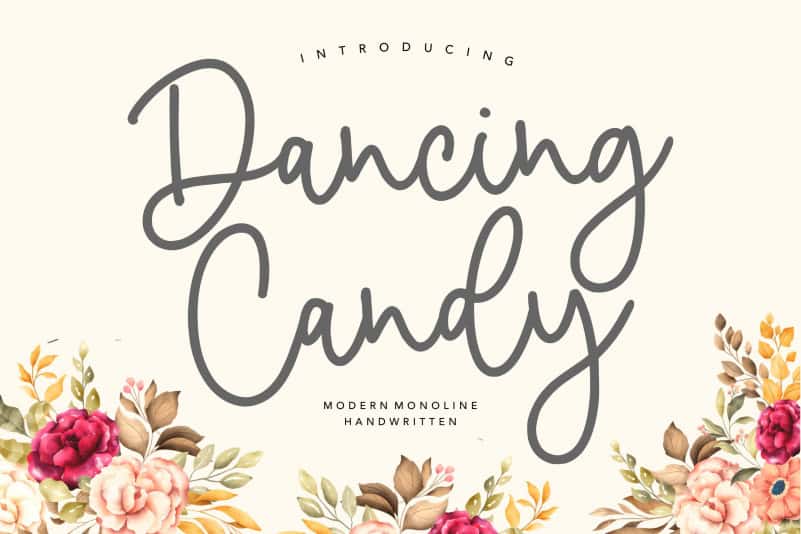
Dancing Candy Handwritten Font – Download Grátis
Aqui está uma descrição apropriada para a página de download da font “Dancing Candy Handwritten Font” para sua categoria de signature fonts: Prestigiosamente apresentamos Dancing Candy Modern Monoline Handwritten Font, um design de fonte elegante e sofisticado que captura a essência do estilo moderno com o charme de uma escrita à mão. Desenvolvida pelo designer balpirick, essa fonte se destaca por seu equilíbrio perfeito entre simplicidade e personalização única. Perfeita para criadores que buscam adicionar um toque singular em seus trabalhos digitais, Dancing Candy atinge o objetivo de manter a essência autêntica da escrita à mão enquanto oferece uma aparência moderna e clara. Suas linhas curvas delicadas e suas formas arredondadas criam um design fluido que convida leitores para navegar através dos textos de forma leve e envolvente. Essa fonte é ideal para designers gráficos, especialmente aqueles buscando incorporar um elemento pessoal em projetos digitais. Seja para criar anúncios impecáveis, folhetos profissionais ou qualquer outro tipo de material digital, Dancing Candy Modern Monoline Handwritten oferece uma maneira elegante e única de expressar a personalidade do seu trabalho. Se você busca uma fonte que combine modernidade com o charme da escrita à mão, Dancing Candy Modern Monoline Handwritten é sua escolha certa.